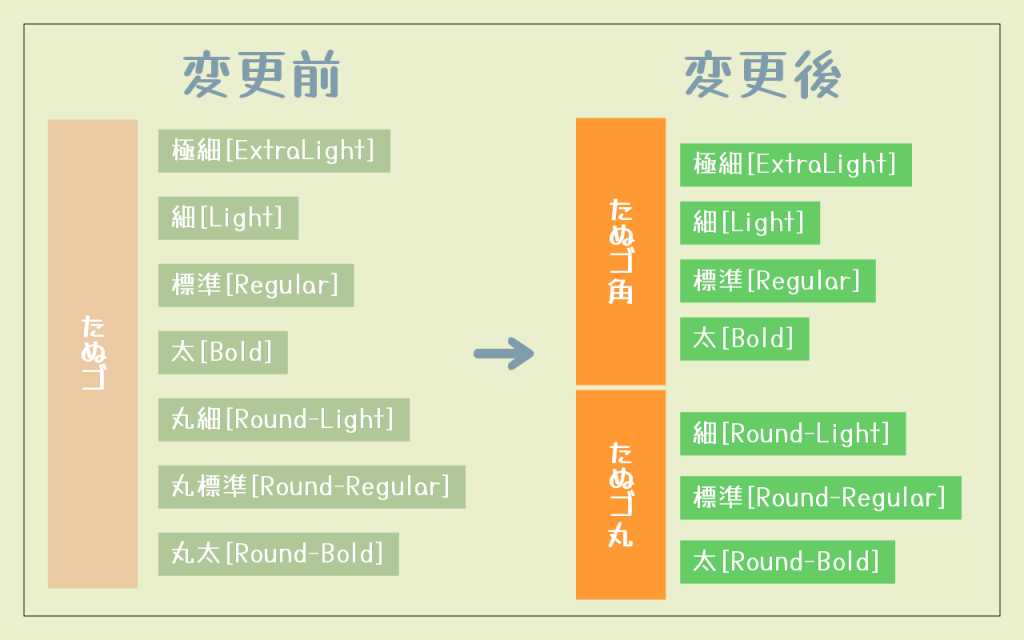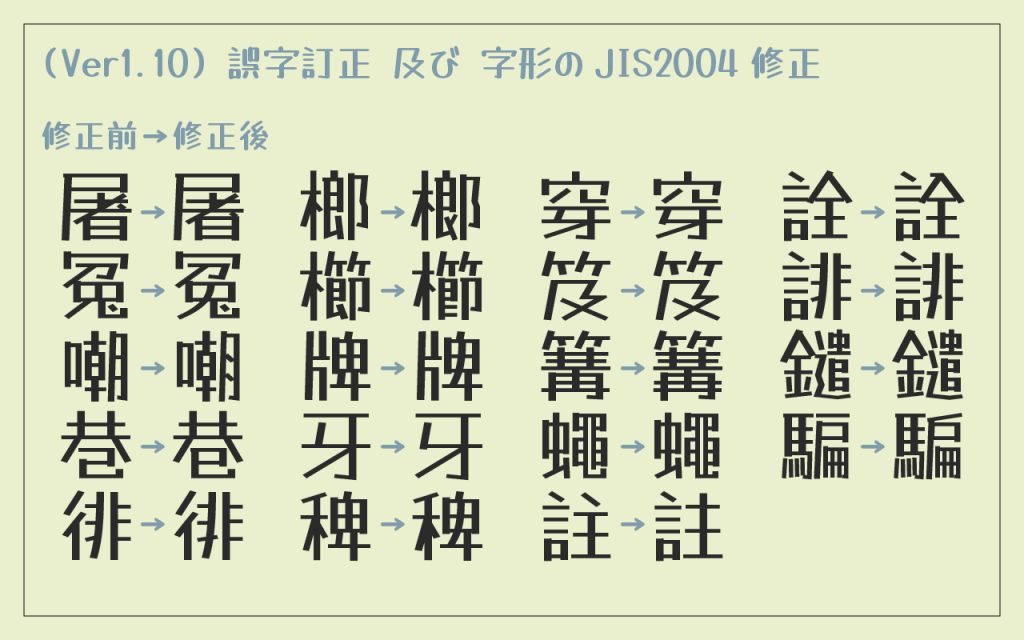
『たぬゴ』ver1.10 アップデートのお知らせ
今回のアップデートには、不具合改善のための大きな変更点として
- フォント名の変更(『たぬゴ』→『たぬゴ角』・『たぬゴ丸』)
があります。
更新内容
【※重要】フォント名を『たぬゴ』から『たぬゴ角』『たぬゴ丸』に変更しました。
フォントの構成を、1つのフォント名で7つのウェイトを持っていた
『たぬゴ』(極細・細・標準・太・丸細・丸標準・丸太)7ウェイト
から、
『たぬゴ角』(極細・細・標準・太)4ウェイト
『たぬゴ丸』(丸細・丸標準・丸太)3ウェイト
という、2つのフォント名でそれぞれ4ウェイト・3ウェイトを持つ構成に分割しました。
誤字の修正を行いました。また、一部の文字をJIS X 0213:2004(JIS2004)例示字形に合わせて修正しました。
誤字修正を行いました。(屠)
字形をJIS X 0213:2004(JIS2004)例示字形に沿うように修正しました。(冤嘲巷徘榔櫛牌牙稗穿笈篝蠅註詮誹鑓騙)
その他の修正
以下の文字を追加しました。「屢」
フィーチャー機能の一部に不足があったので加筆しました。(fwid, vert, vrt2)